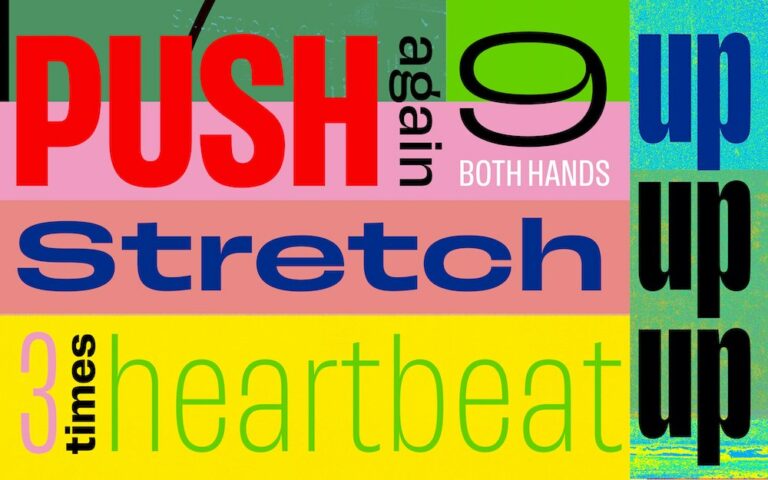
Die Berliner Foundry Fontwerk bietet nicht nur tolle Schriften an, sie hat auch eine besondere Vorliebe für die kreative Zusammenarbeit mit Designbüros.
Als vor etwa einem Jahr der Variable Color Font Hamster erschien, kooperierte Fontwerk mit den schwedischen Top-Kreativen von Snask, die zur Einführung der Schrift eine bunte und vergnügte Kampagne gestalteten.
Dieses Mal wandte sich Fontwerk-Gründer Ivo Gabrowitsch an die Hamburger Agentur Rocket & Wink. Zusammen entwickelten sie eine aufmerksamkeitsstarke, lustige und ebenfalls sehr farbenfrohe Videokampagne.
Bei so vielen bunten Bildern muss man aufpassen, dass die Schrift selbst nicht in den Hintergrund tritt. Das wäre verdammt schade, denn die Schweizer (Type)Designerin Christine Gertsch hat mit Push ein umfassendes Schriftsystem entworfen. Es besteht aus acht Schnitten bei sieben Breiten. Diese 56 Schnitte sind einzeln oder ganz praktisch in einer einzigen Variable-Font-Datei erhältlich. Durch ein ausgeklügeltes Prinzip im Umgang mit ihrer Kurvenbeschaffenheit zwischen XCondensed und XWide, tritt Push in jeder Verfassung selbstbewusst auf und vereint dabei Eigenschaften aus amerikanischen Gothics und europäischen Grotesken.
In der Push finden sich Formanklänge aus den ersten einhundert Jahren der Serifenlosen wieder: ihr schmalfettes G ohne Querbalken ist von Thorowgoods 1830er Seven-Line Grotesque inspiriert, während das kleine a im Geiste der Plak von 1930 erscheint. Ihr Zeichensatz, in dem ein angloamerikanisches Brillen-g, ein zweigeschossiges Grotesk-g sowie ein Dänisches g ohne Schlaufe vorkommen, unterstreicht diese Mischung aus der Neuen und der Alten Welt.
Statt die gesamte Familie einer groß angelegten Interpolationsoperation zu unterziehen, widmete sich Christine Gertsch zunächst den Extremen der fetten Schnitte. Dadurch behielt sie bei der Beschaffenheit der Kurven die Oberhand und vermied arge Kompromisse. Die bewusste Veränderung der Kurvenverläufe ist in der Anatomie von Push ein entscheidendes Merkmal, das sich durch alle Schnitte zieht: von subtilen und doch spannungsvollen Kurven in den ganz engen und leichten Fonts hin zu massiven, selbstbewussten schweren Breiten. Push Regular bewahrt beinahe selbstverständlich einen kühlen Kopf zwischen diesen Extremen.
»Mit Push wollte ich etwas schaffen, das die Grenzen der Möglichkeiten einer variablen Schrift ausreizt, gleichzeitig den Nutzern eine breite Palette von Stilen bietet und den Test der Zeit überdauert,« so Christine Gertsch. »Es war mir eine Herzensangelegenheit, eine Schrift zu schaffen, die unter allen Bedingungen gut funktioniert.«